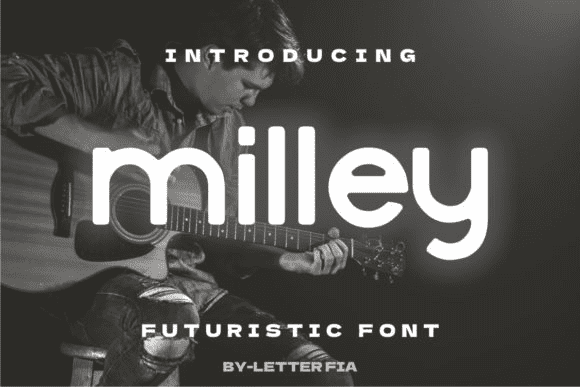
Название: Milley Font
Milley - простой и футуристический шрифт без засечек.
Независимо от темы, этот шрифт будет невероятно полезен в вашей библиотеке шрифтов, поскольку он способен возвысить любое творение.